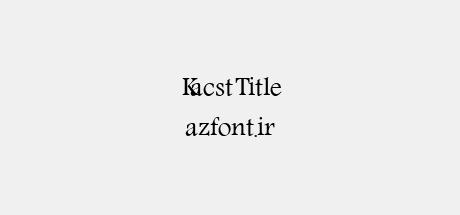
فونت زیبای رایگان KacstTitle
قلم زیبای KacstTitle از سری قلم های بسیار زیبا برای تایپوگرافی و لوگو تایپ می باشد.این قلم در وزن KacstTitle و توسط Maurice Jabre طراحی و منتشر شده است.